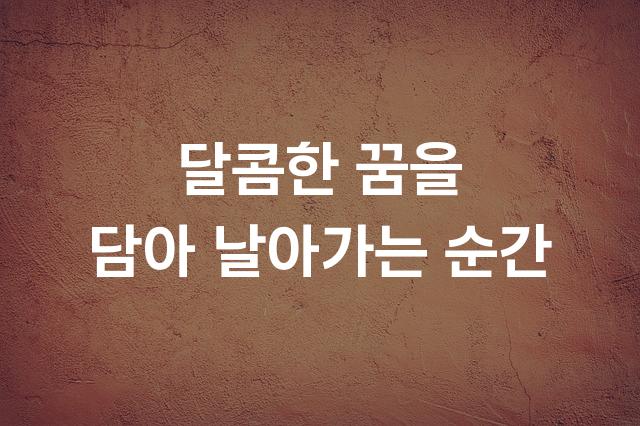
‘플라이트 산스 Title’은 제주항공에서 제작한 기본 고딕 스타일의 폰트로, 제목용으로 최적화된 꽉 찬 고딕 디자인을 자랑합니다. 장식적 요소가 더해진 고딕체로서, 모던하면서도 강렬한 인상을 줍니다.
플라이트 산스 Title은(는)
별모양/패턴, 길고/크고, 기본 고딕, 부드러움, 단단함, 감성적인, 장식 스타일, 굵은 고딕 계열의 생김새를 가지고 있으며
로고 디자인, 제품 포장, 브랜딩 등에서 자주 활용되며, 효과적인 메시지 전달에 적합합니다.
이 폰트는 광고/마케팅, 크리에이티브, 패션/뷰티 분야에 잘 어울리며,
고급스러운, 전문적인, 세련된 느낌을 담고 있는 것이 특징입니다.